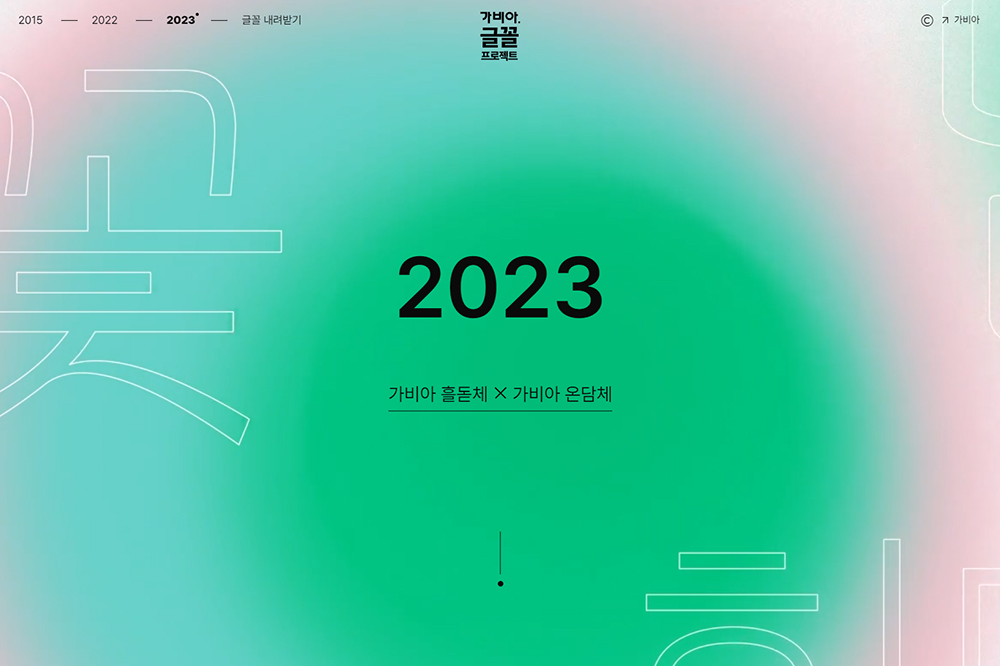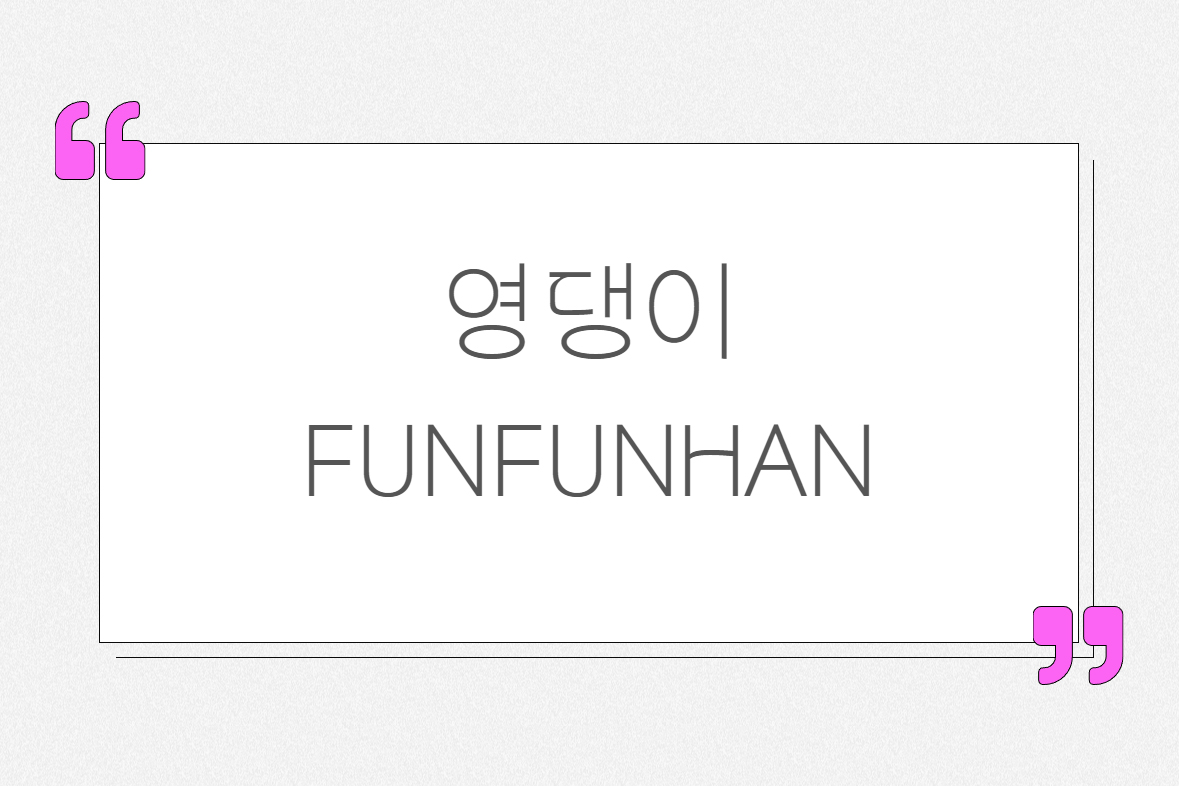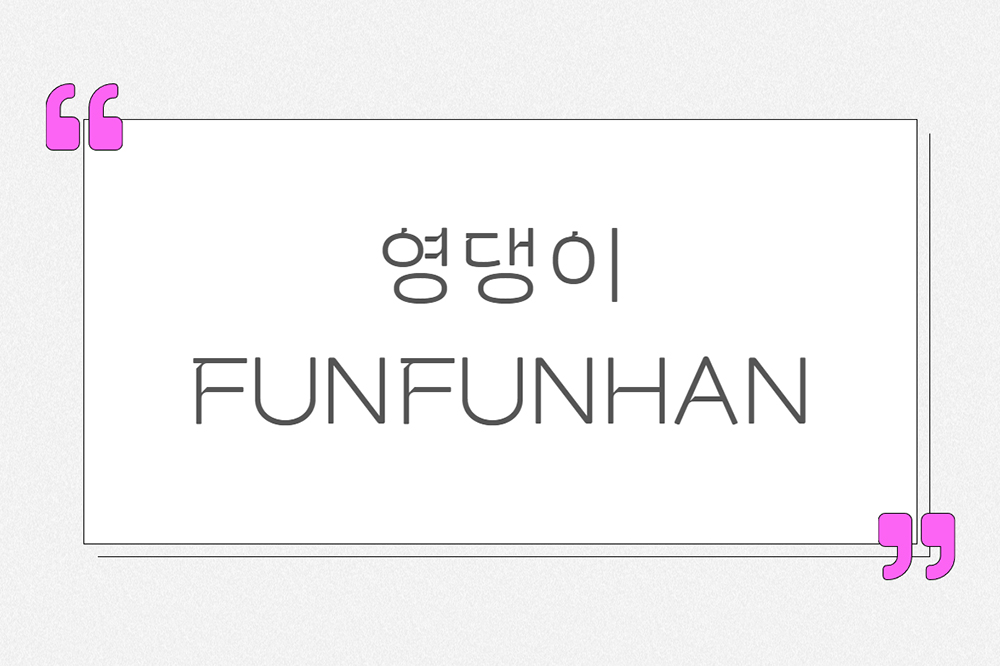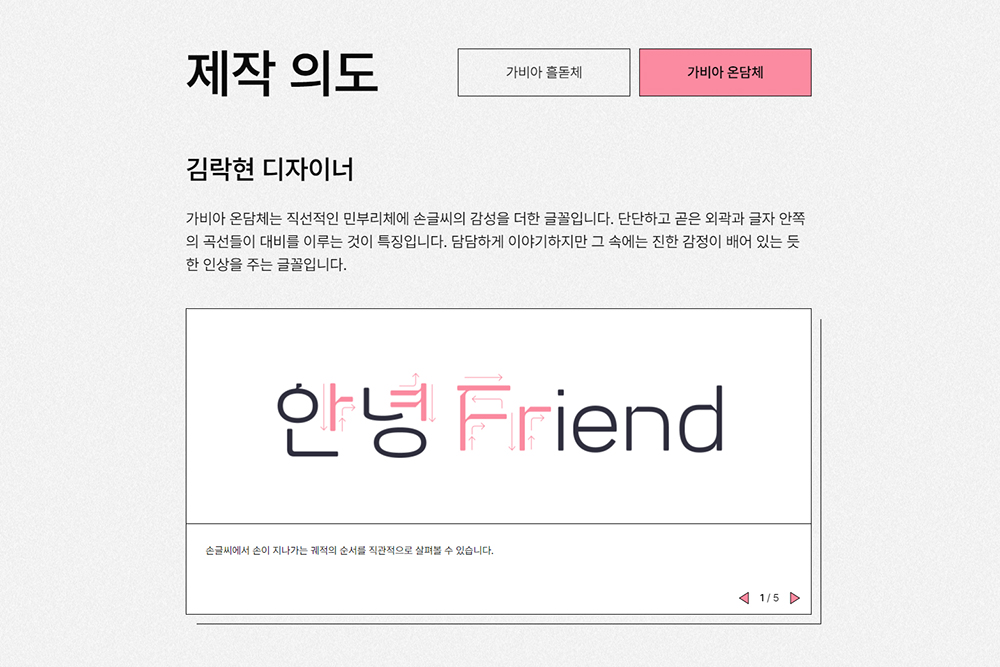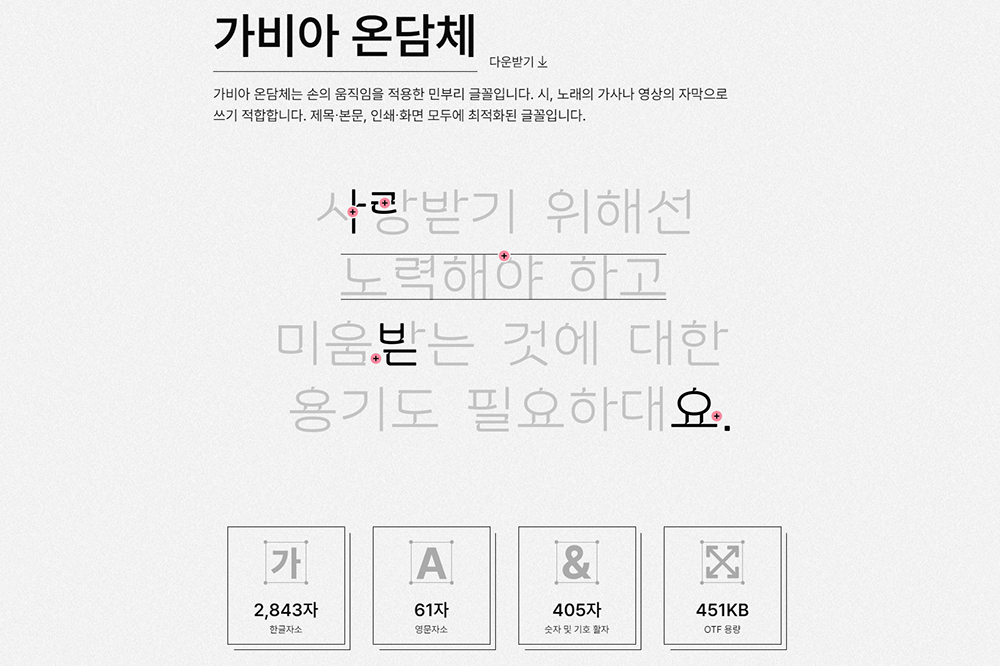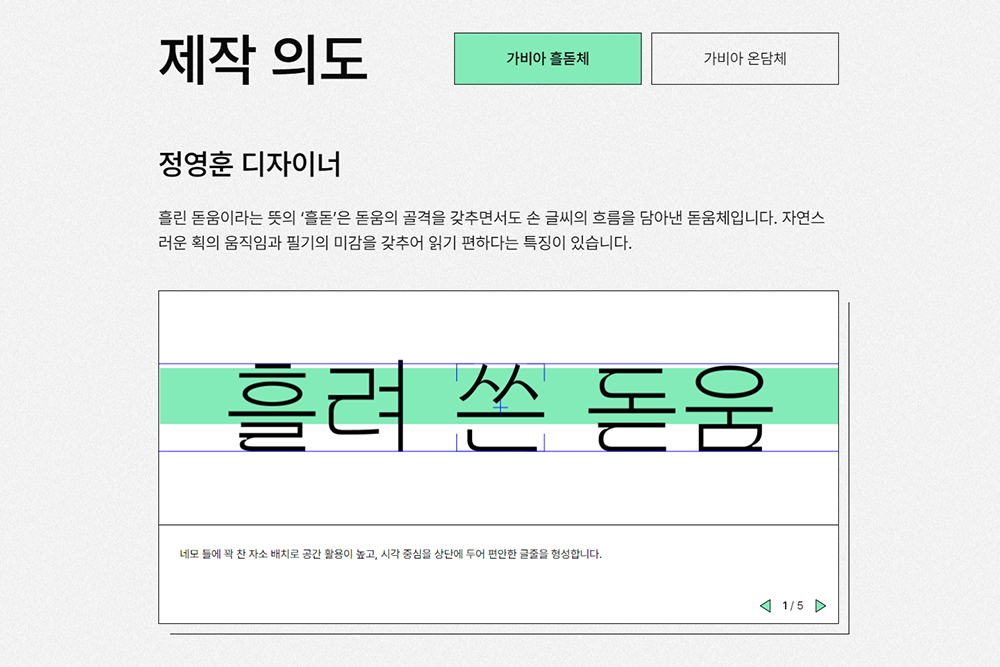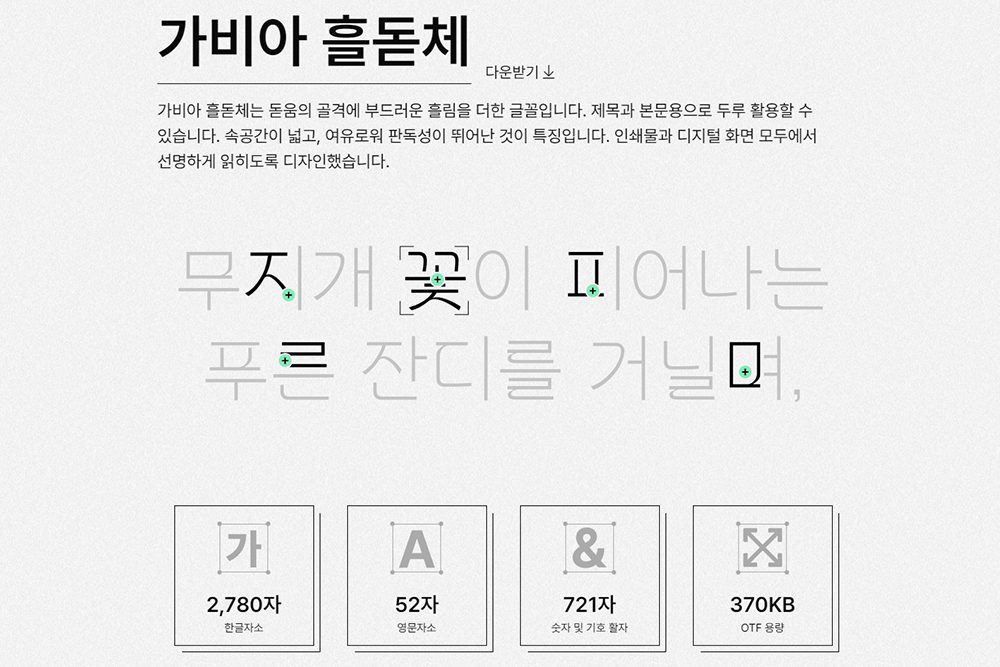
콘텐츠를 제작할 때 은근히 신경이 쓰이는 부분 중의 하나는 바로 폰트라고 할 수 있습니다. 특히 최근에는 라이센스 관련 문제들 때문에 안전하고 세련된 폰트들이 얼마나 많이 파악하고 있느냐가 일종의 경쟁력이 되기도 합니다. 그럼 이번 포스팅에서는 무료로 활용할 수 있는 가비아 글꼴 프로젝트의 흘돋체와 온담체에 대해서 자세하게 확인해 보도록 하겠습니다.
우선 가비아 흘돋체의 경우에는 정영훈 디자이너에 의해서 제작되었고 흘린 돋움이라는 뜻의 ‘흘돋’은 돋움의 골격을 갖추면서도 손 글씨의 흐름을 담아낸 돋움체라고 합니다. 제목이나 본문 용으로 두루 사용하기 편리하고 2,780자의 한글자소와 52자의 영문자소 그리고 721자 숫자 및 기호 활자를 제공합니다.
가비아 온담체의 경우에는 김락현 디자이너에 의해서 제작되었습니다. 직선적인 민부리체에 손글씨의 감성을 더한 글꼴이라고 합니다. 흘돋체와 마찬가지로 제목이나 본문용으로 사용하기에 적합합니다. 참고로 2843자의 한글자소와 61자의 영문자소 그리고 405자 숫자 및 기호 활자로 구성되어 있습니다.